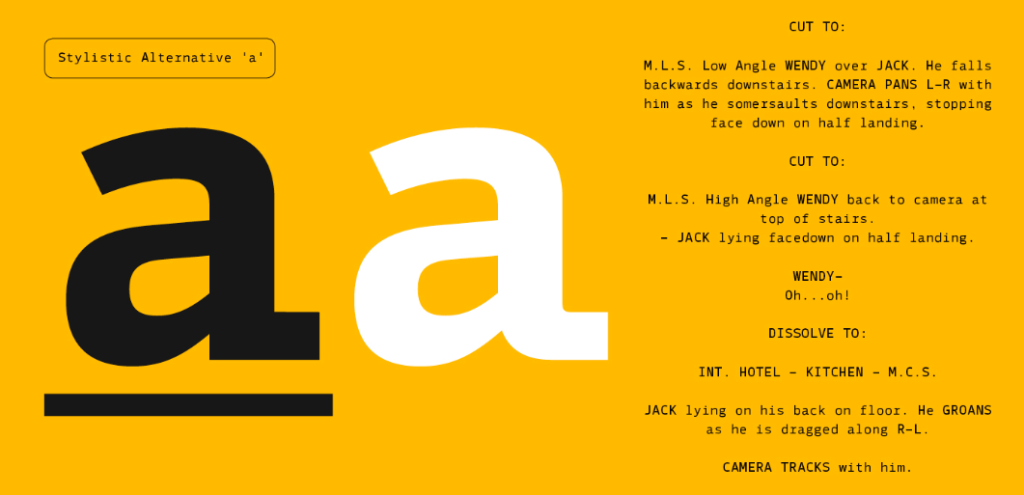
Kiểu chữ: Monospace
Mono Font là kiểu chữ có các ký tự với chiều rộng bằng nhau, thường được sử dụng trong lập trình và thiết kế đòi hỏi tính chính xác cao. Với phong cách đơn giản, thuộc bộ font chữ không chân nên Mono Font dễ đọc và cấu trúc đồng nhất, không chỉ phù hợp cho mã nguồn mà còn được ưa chuộng trong các thiết kế mang đậm chất công nghệ và tối giản. Cùng tìm hiểu về những đặc điểm nổi bật của phông chữ Mono và cách áp dụng chúng trong các dự án sáng tạo để đạt hiệu quả tối đa.